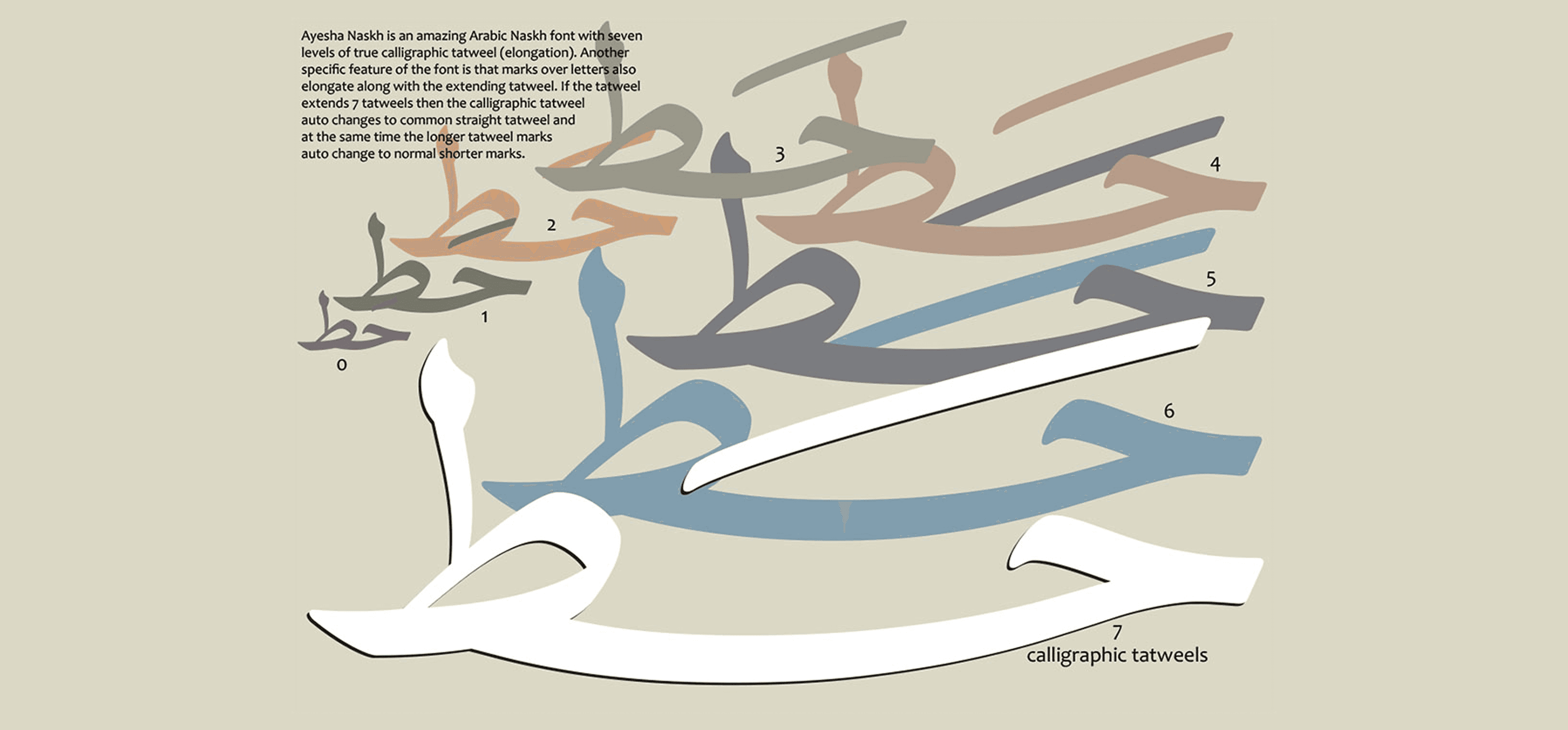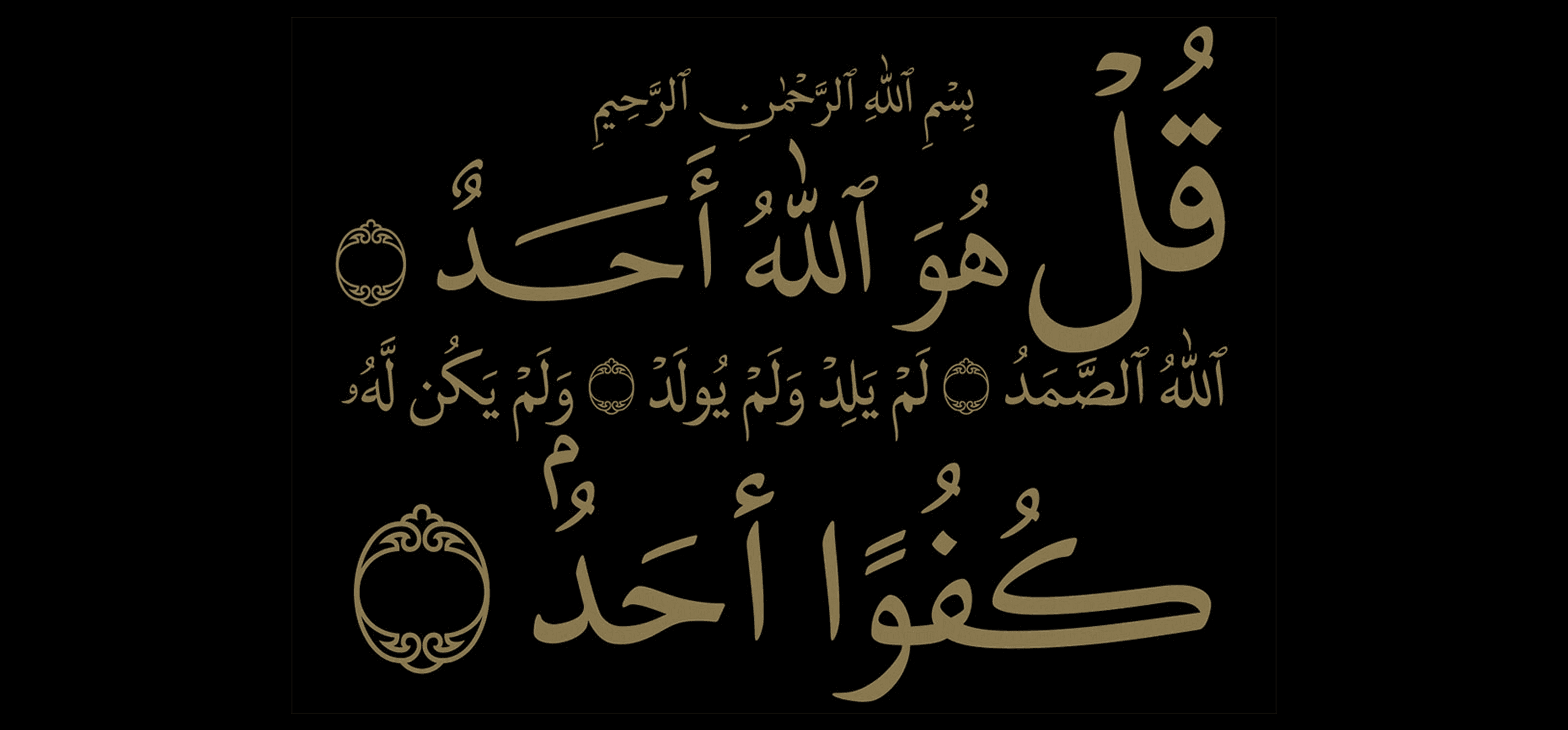
عايشة نسخ هو الإصدار الأصغر من خط عمر نسخ. بينما يغطي عمر نسخ عددًا كبيرًا من اللغات، يركّز عايشة نسخ على اللغة العربية فقط.
ومع ذلك، يتمتع عايشة نسخ بعدة مزايا مقارنة بعمر نسخ، مثل سرعته العالية بفضل حجمه الصغير، وجود عمل دقيق في المسافات بين الحروف (kerning)، بالإضافة إلى أشكال خاصة إضافية للنصوص القرآنية.
يحتوي على جميع الميزات الأخرى الموجودة في خط عمر نسخ، ولذلك يُنصح باستخدام عايشة نسخ في الأعمال المخصصة للغة العربية فقط.